فونتهای فارسی یکی از مهمترین عناصر طراحی گرافیکی هستند که میتوانند زیبایی و جذابیت محتوای شما را افزایش دهند. اما پیدا کردن فونتهای فارسی با کیفیت و رایگان ممکن است کار سختی باشد. برای همین، ما در این مقاله ۷ فونت فارسی رایگان را برای شما انتخاب کردهایم که میتوانید آنها را از همین جا دانلود کرده و در پروژههای خود استفاده کنید.
معرفی ۷ فونت فارسی رایگان
اسطوری
این فونت فارسیسازی شدهی فونت اسطوره که فونت عربیست میباشد. در این فونت حروف گچپژ اضافه شده است و شما میتوانید تمامی متن فارسی را بوسیله این فونت زیبا تایپ نمایید.
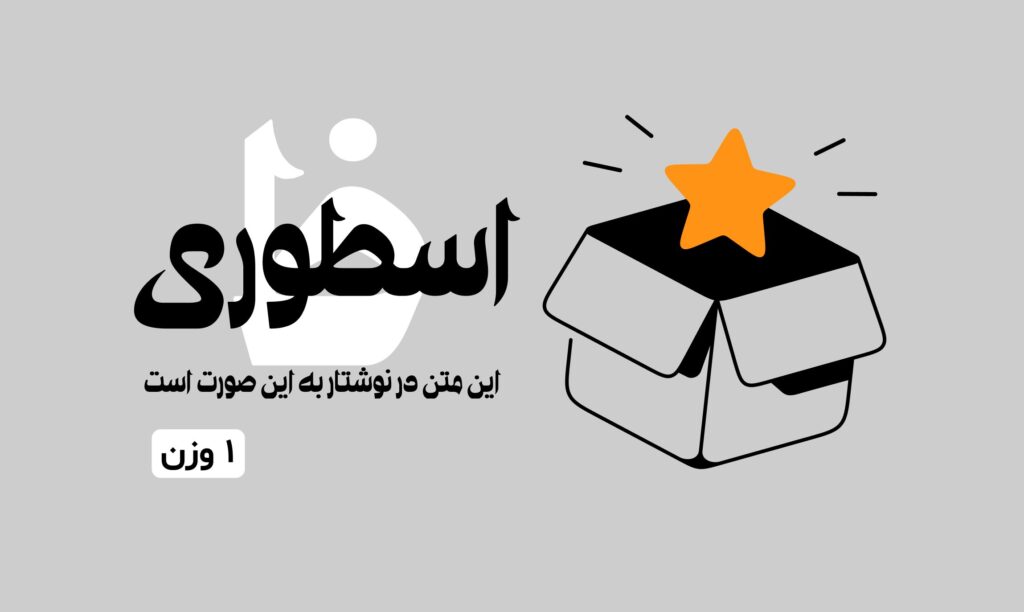
شبنم
فونت شبنم، از فونتهای رایگان فارسی است که با آن میتوانید صفحهآرایی های زیبایی را خلق کنید. طراحی این فونت به نحوی است که خوانایی بسیار بالایی را به متن شما میبخشد.
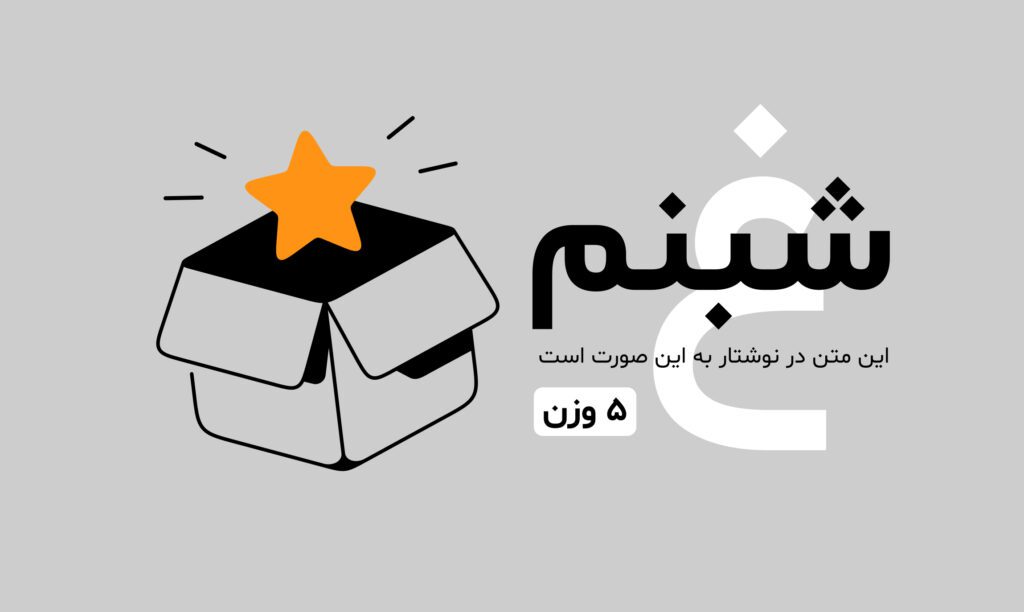
استعداد
فونت استعداد فونتی مناسب برای یک طراحی مینیمال و ساده است. وزنهای مختلف این فونت باعث میشود دست شما در استفاده از این فونت هم در متن و هم در عناوین باز باشد.
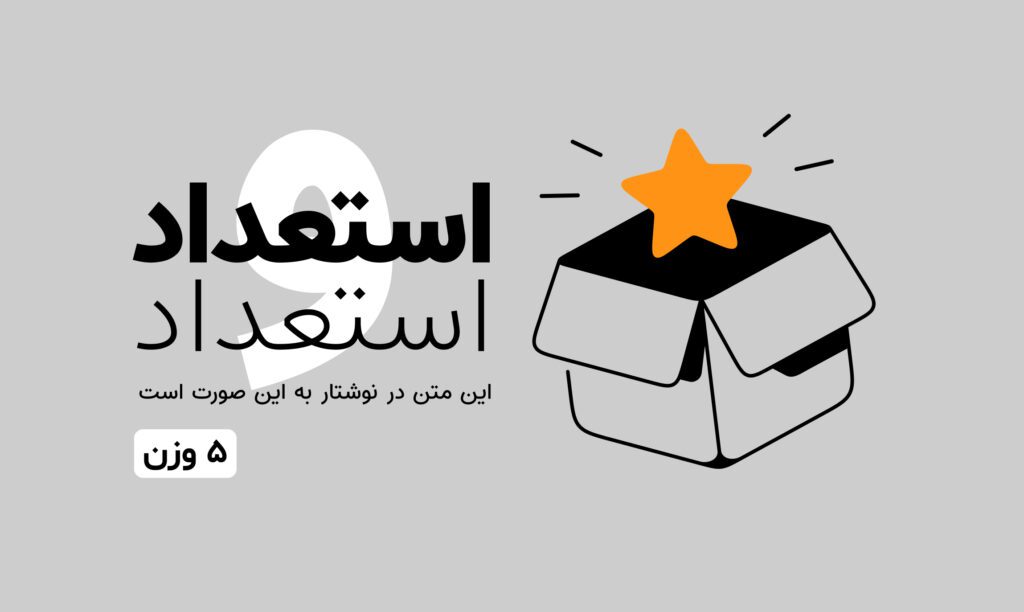
لتلک
فونت لتلک از فونتهای عربی است که به دلیل شباهت رسم الخط فارسی و عربی، میتوان از آن در نوشتن متنهای فارسی هم استفاده کرد.
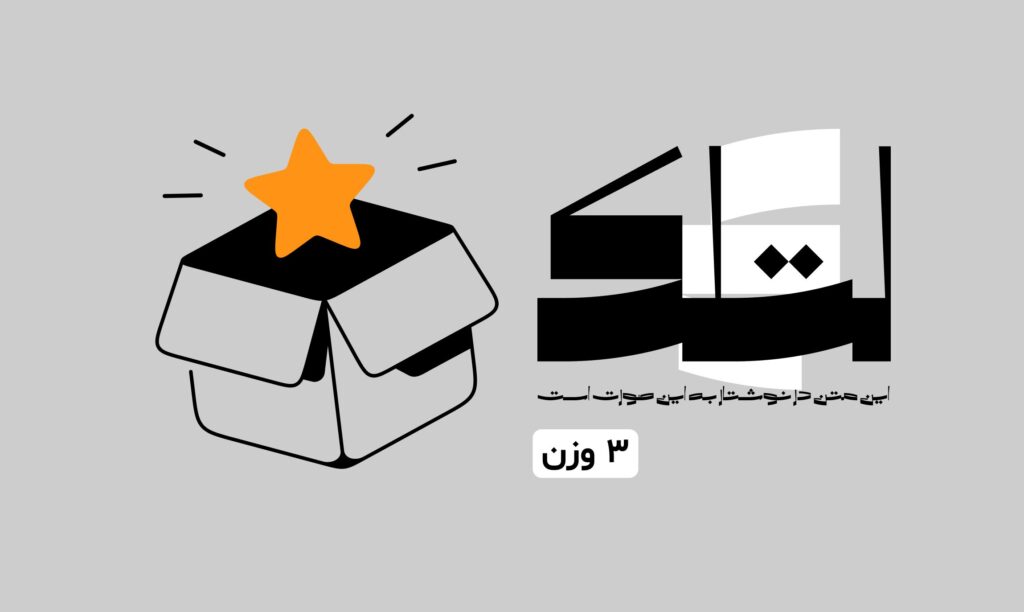
قاف
فونت قاف را شاید تا کنون در طراحی پوسترهای مختلف دیده باشید. استفاده از این فونت در عناوین، جذابیت خاصی به طراحی های شما خواهد بخشید.
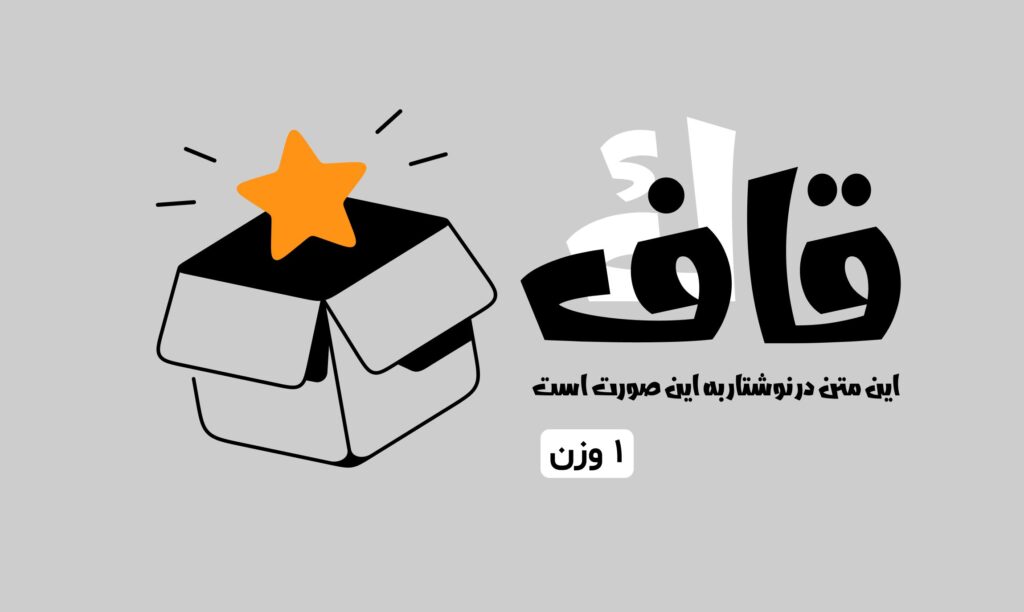
دیودرام عربیک
کمتر فونتی مانند دیودرام عربیک را میتوان یافت که به شما امکان تایپ به زبان های مختلف را بدهد. شما با استفاده از این فونت میتوانید به زبان های فارسی انگلیسی و عربی به صورت همزمان تایپ کنید. این فونت دارای 6 وزن مختلف است.
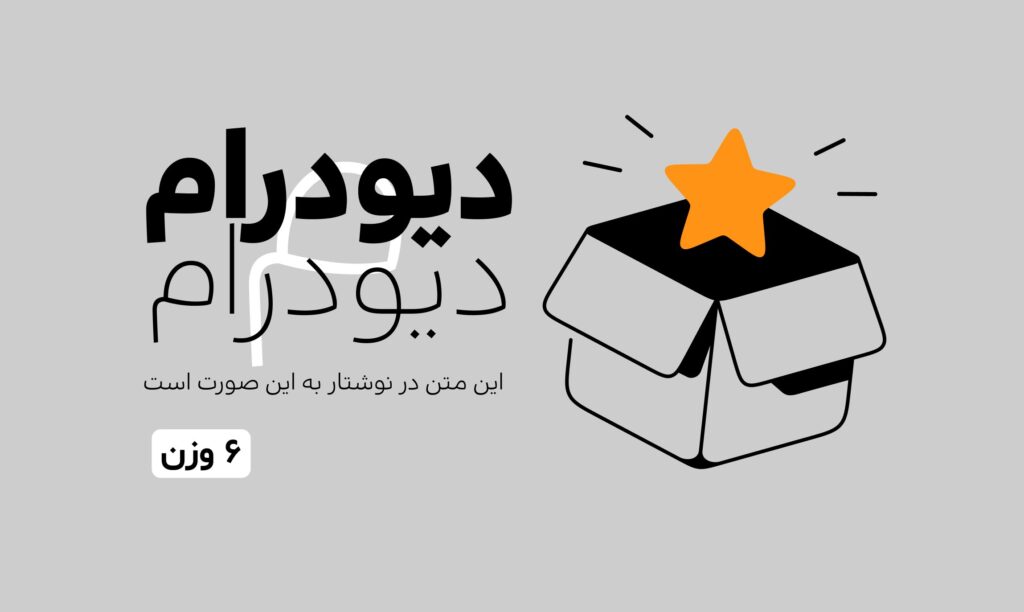
ملصق
یکی دیگر از فونتهای عربی که به شما امکان تایپ فارسی را میدهد فونت ملصق است. شما از این فونت برای نوشتن عناوین خود و یا متن های کوتاه میتوانید استفاده کنید.